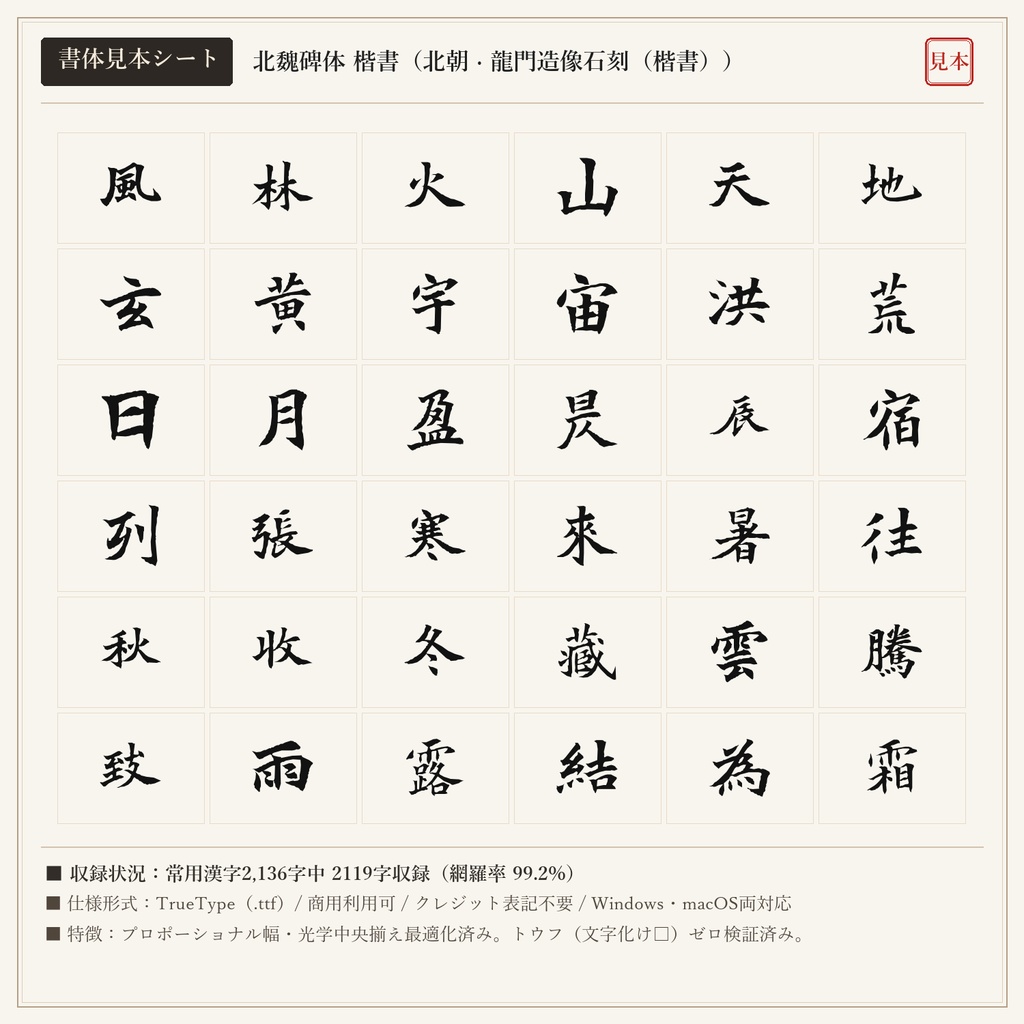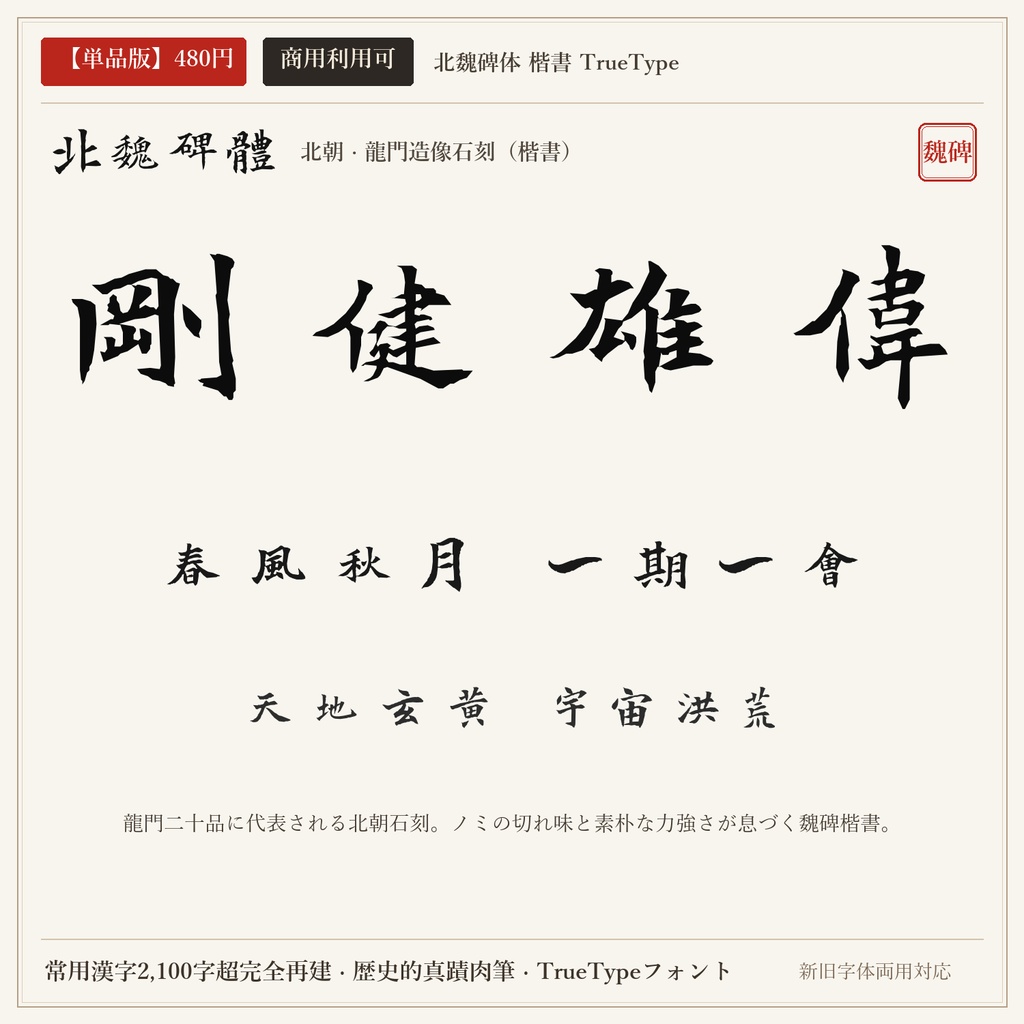
【単品版】北魏碑体 楷書フォント|北朝石刻の刀筆・野性剛健の石門銘・商用利用可
北魏時代の龍門造像銘や張猛龍碑などの石刻文字から抽出・再建した楷書フォントです。紙上の筆墨とは一線を画す、ノミで刻み込まれた鋭い直線、角張った方筆、野性味あふれる力強さを体感できます。 ■ 本フォントの特徴 ・常用漢字2,136字中、2119字を高精度収録(網羅率 99.2%)。 ・現代の新字体を入力しても、歴史的な真蹟字形・旧字体が自然に出力されるデュアルマッピング対応。 ・文字ごとの最適なプロポーショナル字幅設定により、自然で流麗な連綿と墨の息遣いを再現。 ・トウフ(文字化け□)を出さない事前フォントマッピング検証済み。 ■ 未収録文字一覧(全17字) 歴史的真蹟・拓本に存在しない以下の字種は未収録(非対応)となります。ご購入前にご確認ください。 丼 厘 峠 扱 拶 枠 栃 桁 濫 碁 線 脊 著 込 郷 闘 駄 ■ 形式 TrueTypeフォント(TTF) / Windows・macOS両対応 ■ 利用規約 個人・法人の商用利用OK。クレジット表記不要。 ロゴ、動画、ゲーム、書籍、同人誌、配信サムネイル、Web、印刷物、グッズ等に自由にご使用いただけます。 フォントファイル自体の再配布・共有・販売・転売は禁止です。 ※東晋の王羲之(行書)と盛唐の顔真卿(楷書)を同梱した「【無料版】王羲之 + 顔真卿 2書体セット(0円)」もショップ内にて無料配布中です。